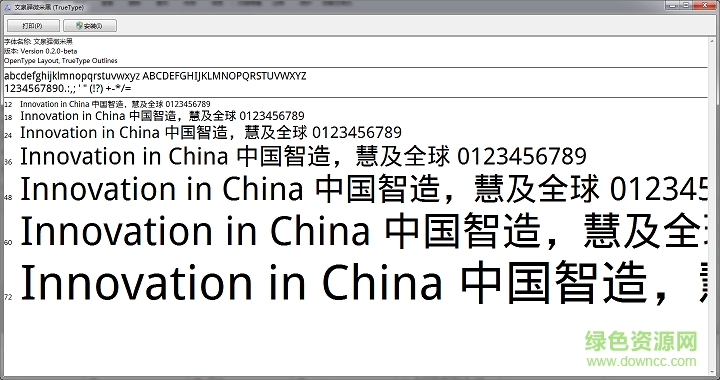
文泉驛自由字體是一款字形方正的中文簡(jiǎn)體字體,多用于廣告設(shè)計(jì)、創(chuàng)意制作、排版制作等領(lǐng)域,使用比較廣泛,喜歡的朋友,而且整個(gè)字體看起來(lái)十分的大方,印刷起來(lái)也很好看,非常的不錯(cuò),趕快下載體驗(yàn)吧!
該字體包含了所有常用簡(jiǎn)體中文、繁體中文,日文及韓文所需要的漢字(最新版本包含超過(guò)27842個(gè)漢字,完整覆蓋GB2312/Big5/GBK/GB18030標(biāo)準(zhǔn)字符集)。該字體同時(shí)還包含了英文、日文、韓文和其他多種語(yǔ)言符號(hào)。